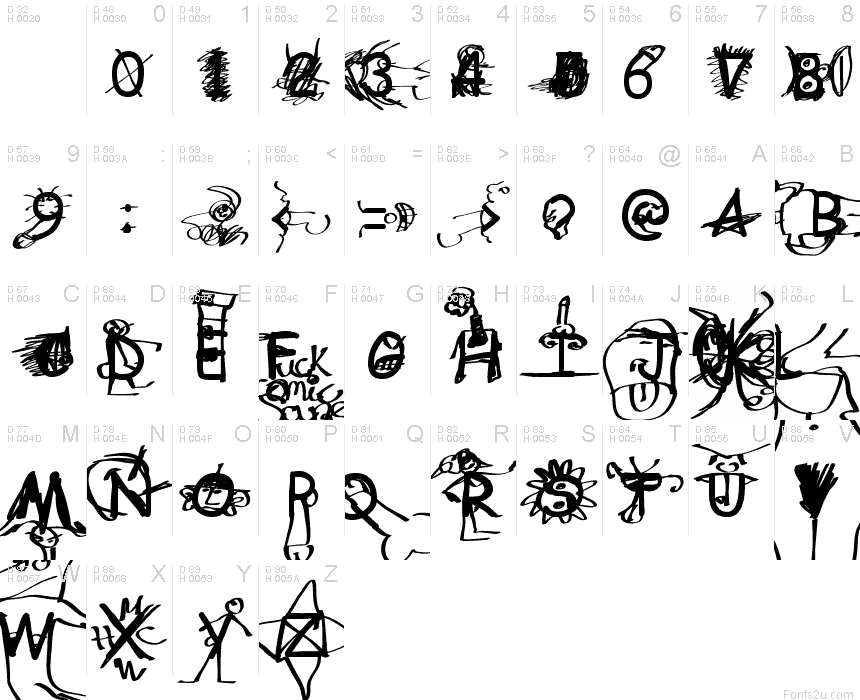
fuckSansJODER من Tuvieja Lagalga هو خط عرض (display) مجاني مشوه يشبه نوبة غضب مصورة بحبر أسود سميك. تتصادم الحروف ببعضها البعض، وتبرز للخارج، وتتشابك في حلقات مبعثرة، مما يمنح كل كلمة طابعاً خاماً وجريئاً. لا يوجد شيء أنيق أو مهذب هنا، فقط خطوط فوضوية، ووزن غير متساوٍ، وشعور بأن النص قد يزحف خارج الصفحة في أي لحظة.
باستخدام fuckSansJODER، ستحصل على طاقة صاخبة وفوضوية تترك أثراً قوياً على ملصقات حفلات البانك، وأغلفة ألبومات النويز (Noise) أو الموسيقى التجريبية، والمجلات البديلة (Zines)، وعناوين فن الجليتش (Glitch-art)، ورسومات الاحتجاج، وتصاميم علامات الشارع (Streetwear). يتألق هذا الخط المجاني عند استخدامه بأحجام كبيرة، حيث تتحول الخطوط المتداخلة إلى نسيج كثيف يشبه كتابات الجدران. وللحفاظ على القراءة المريحة، قم بإقرانه بخط بلا زوائد (Sans Serif) بسيط وضيق، واترك fuckSansJODER للعناوين الرئيسية أو الكلمات المنفردة التي تريد إبرازها.